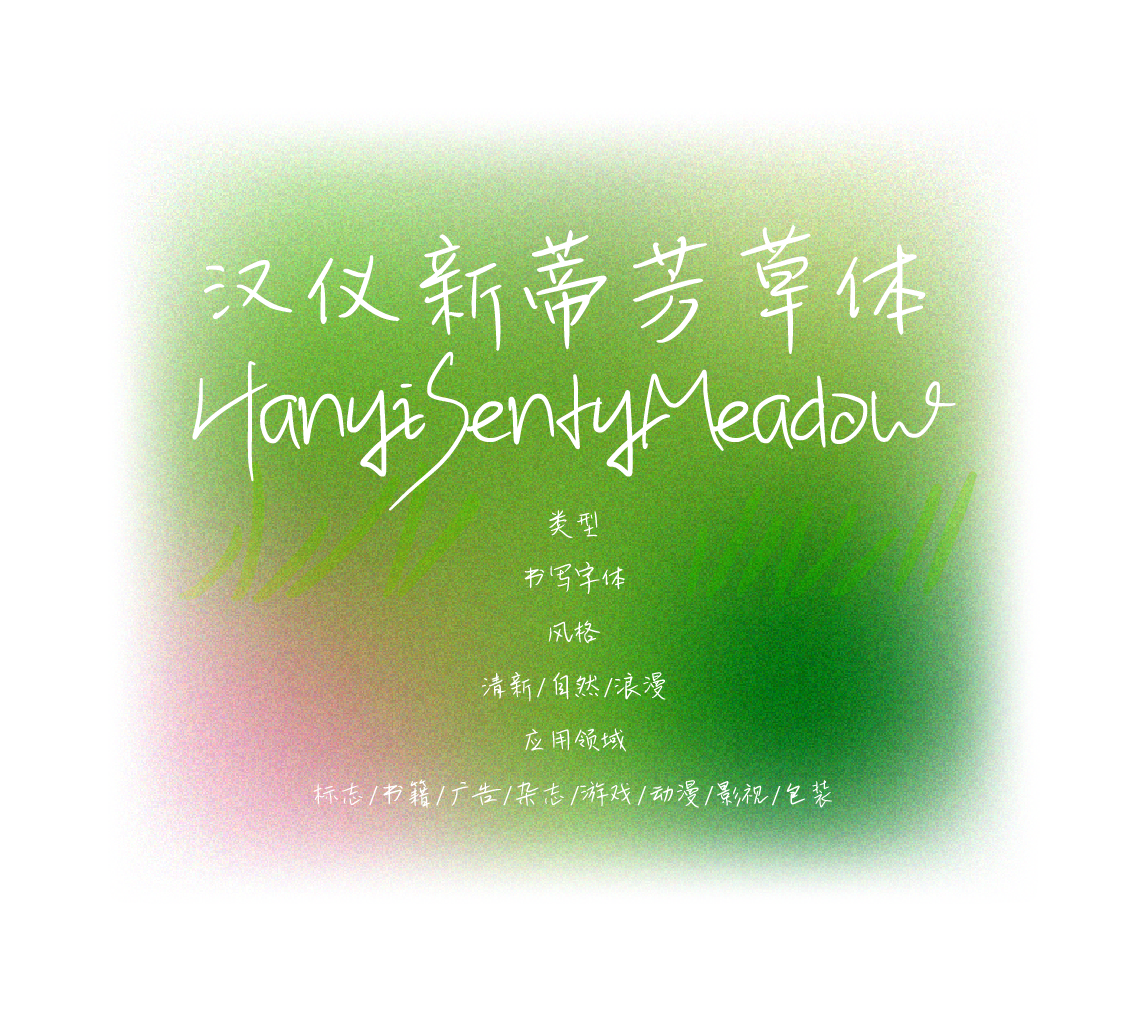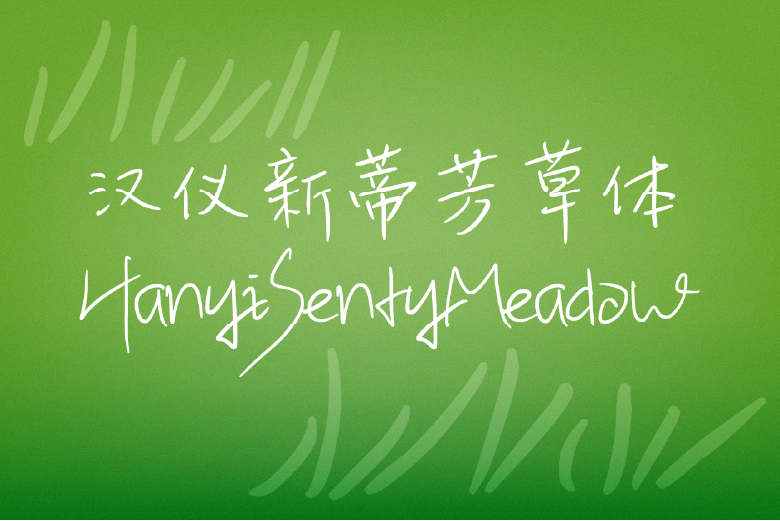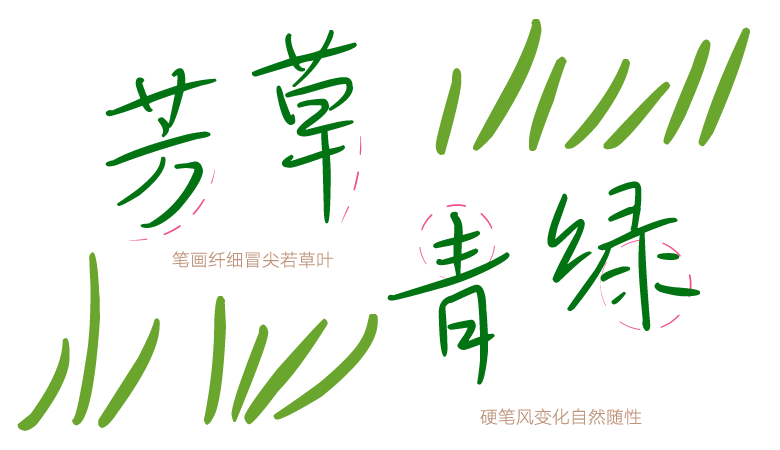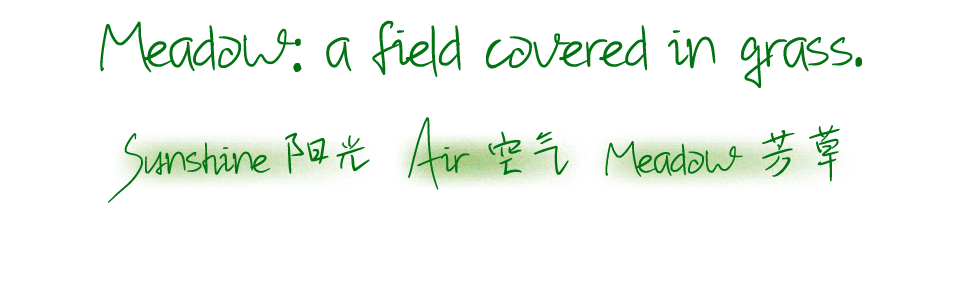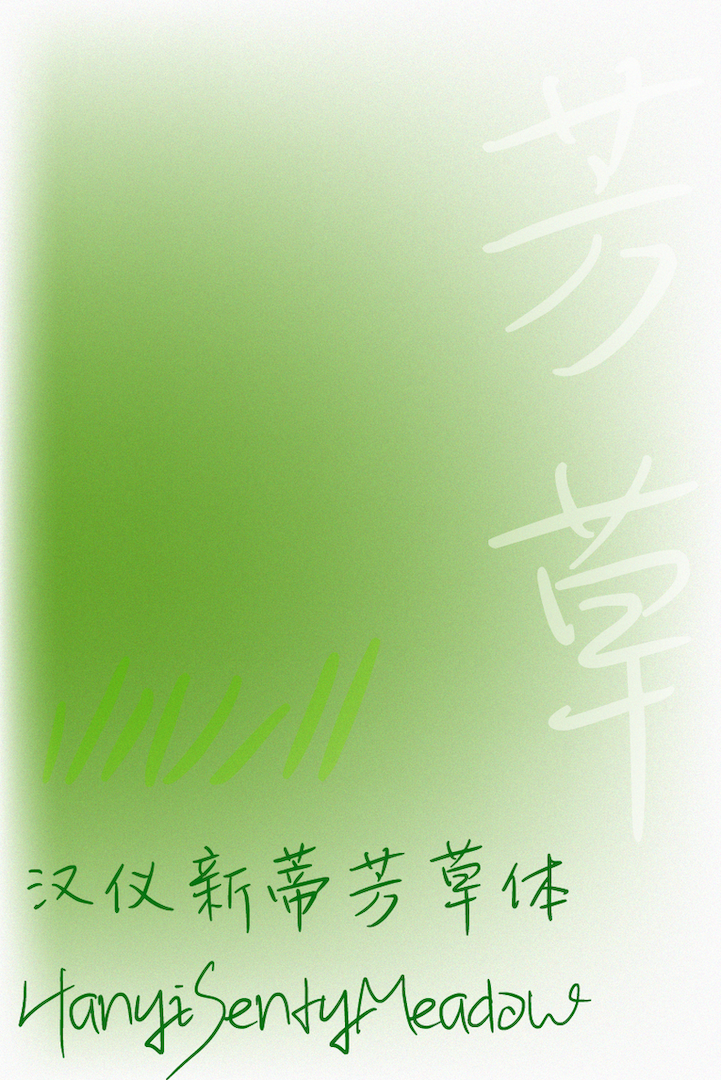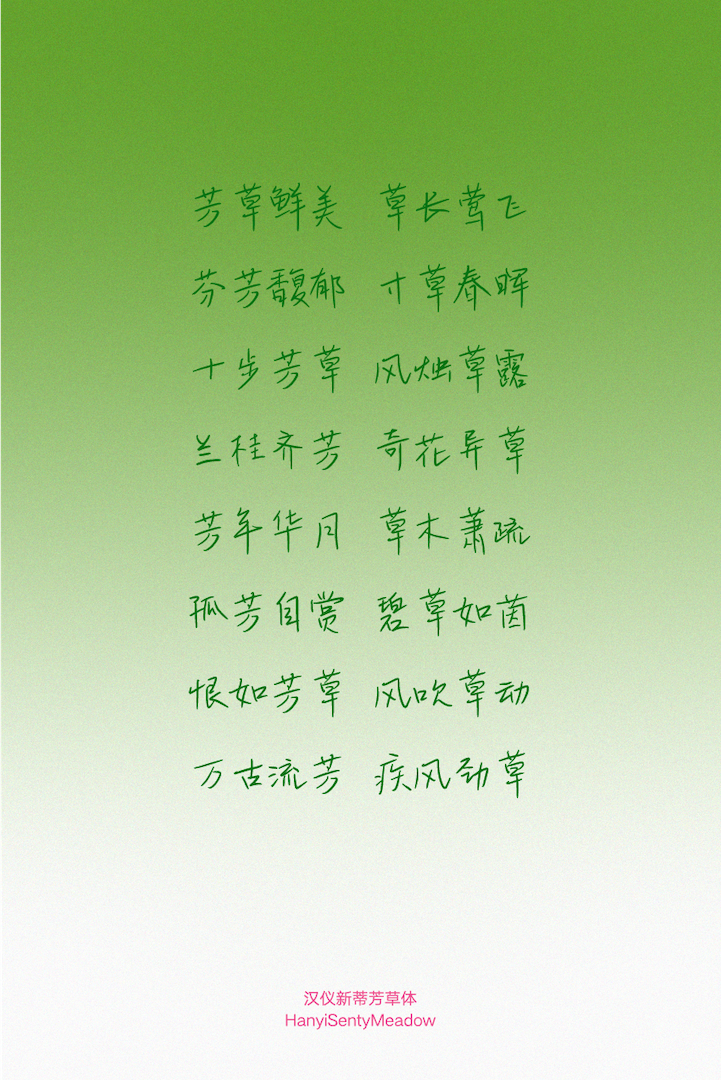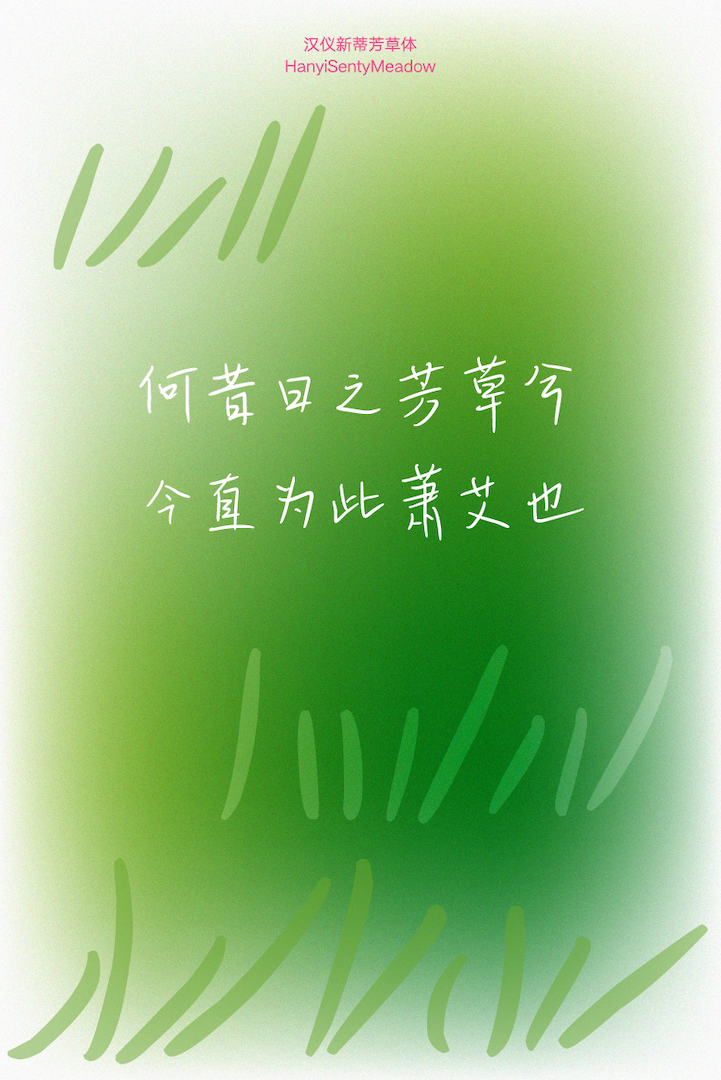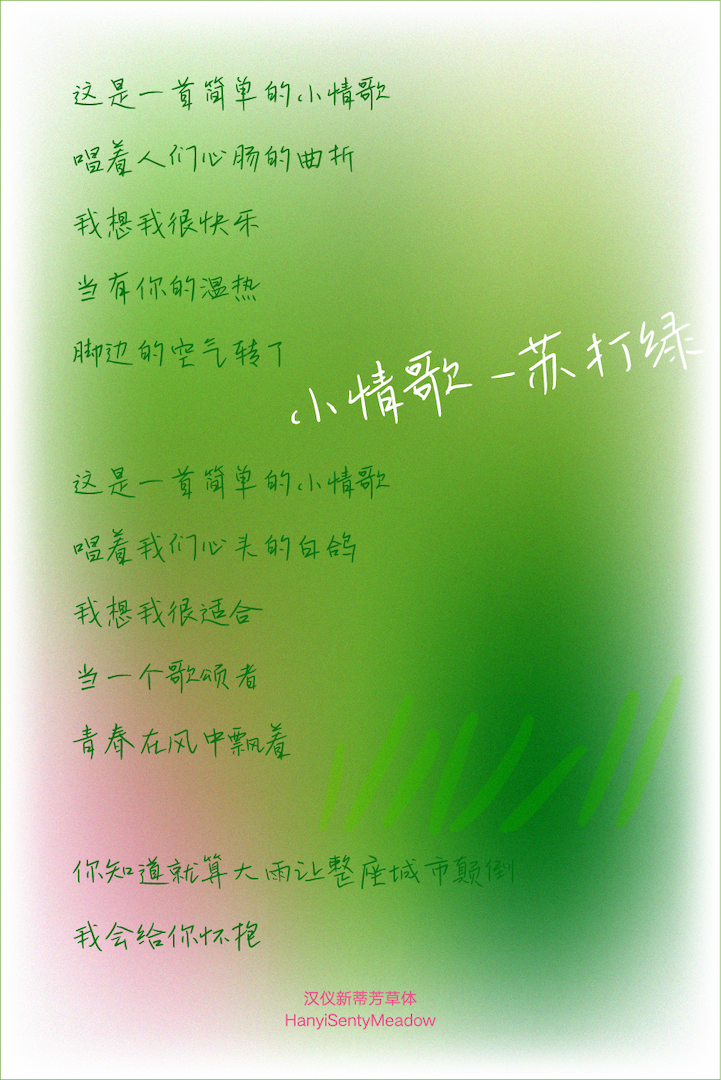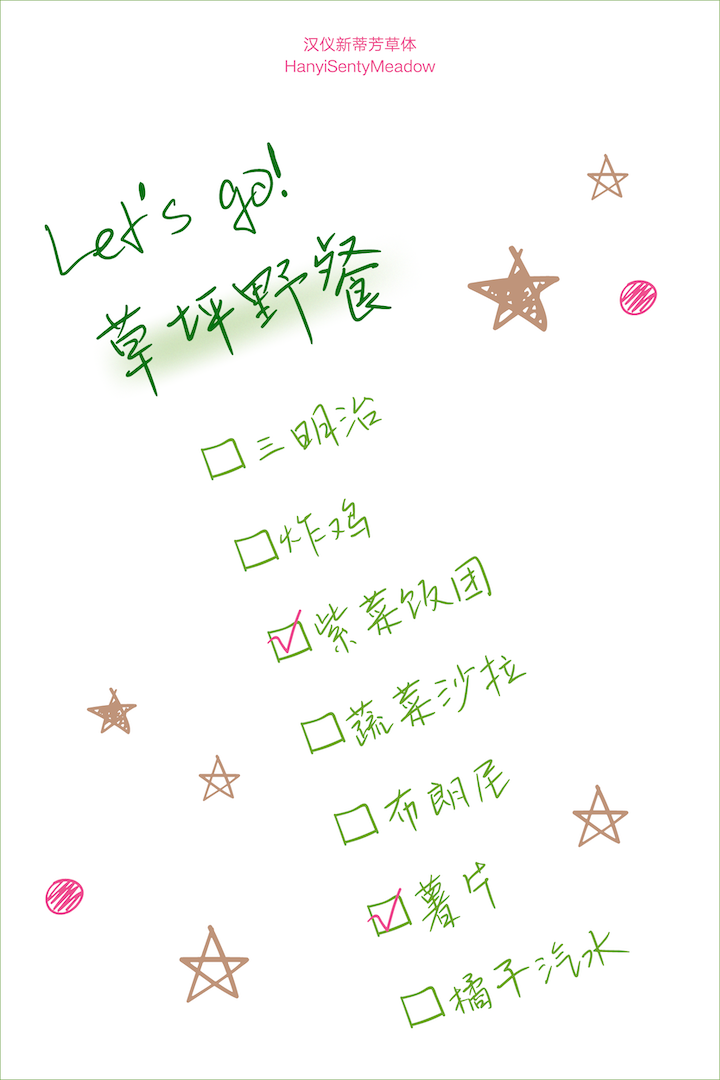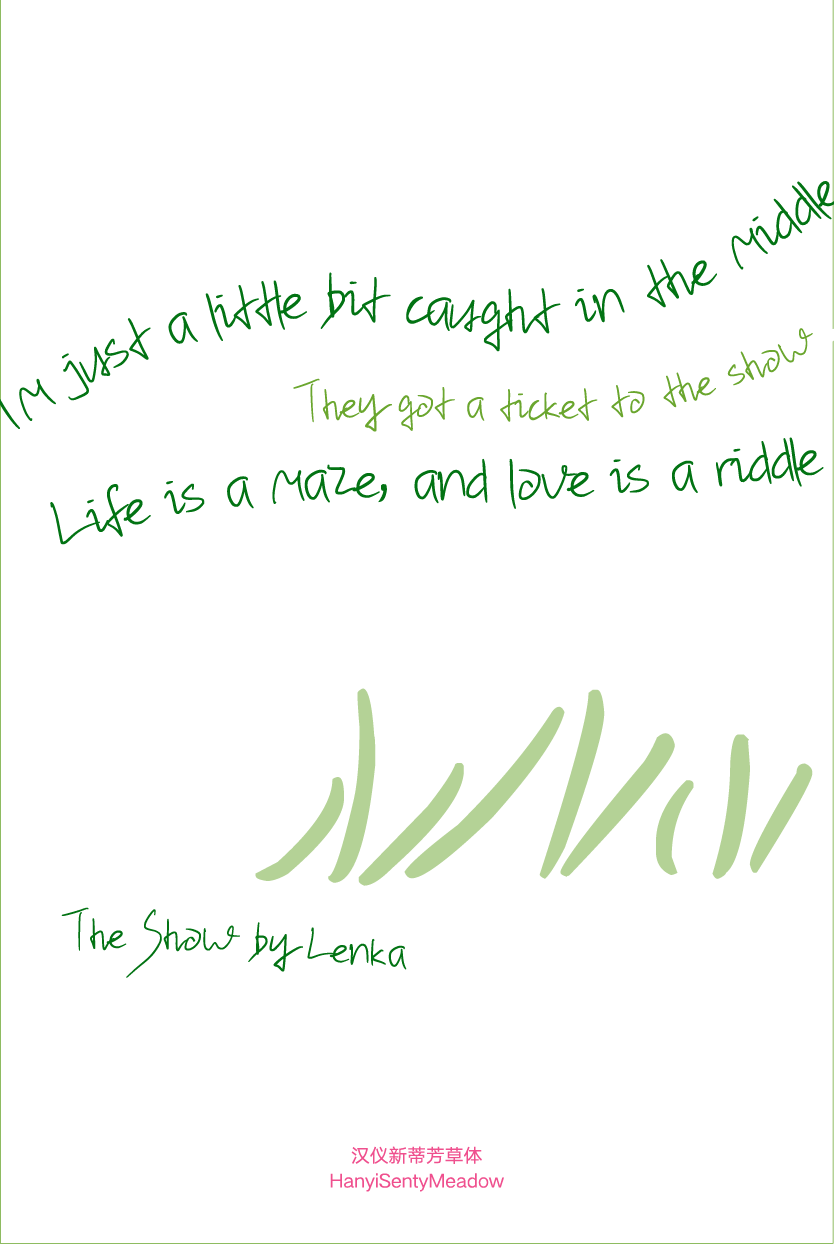
汉仪新蒂芳草体
汉仪新蒂芳草体是一款清新自然的手写字体。笔势均向右提收而产生律动感,犹如被微风吹拂着的青青草地般充满生机。城市里充满噪音,就连城市里的各种字体也要大声疾呼才能被人看到,而汉仪新蒂芳草体在这样的喧嚣之中就如同一片绿洲,带来了一阵清新的风,让躁动的心灵平静下来,聆听芳草低语。这款字体适合用作小字号的副标题和较短的文案,富于变化,应用于清新浪漫、自然悠闲的场景。
汉仪新蒂芳草体的字形偏窄偏长,字面大小不一,随字形而变化,像芳草那样郁郁生长着。
汉仪新蒂芳草体是一款硬笔风格的手写字体,纤细的笔画变化自然随性,笔锋若草叶一般冒出尖尖。
笔势均向右提收,产生律动感,如同被微风吹拂着的青青草地。
汉仪新蒂芳草体的西文部分与中文部分的设计语言一致,笔画呈现出有生命力的变化,笔势向右提收,中西文搭配清新自然。